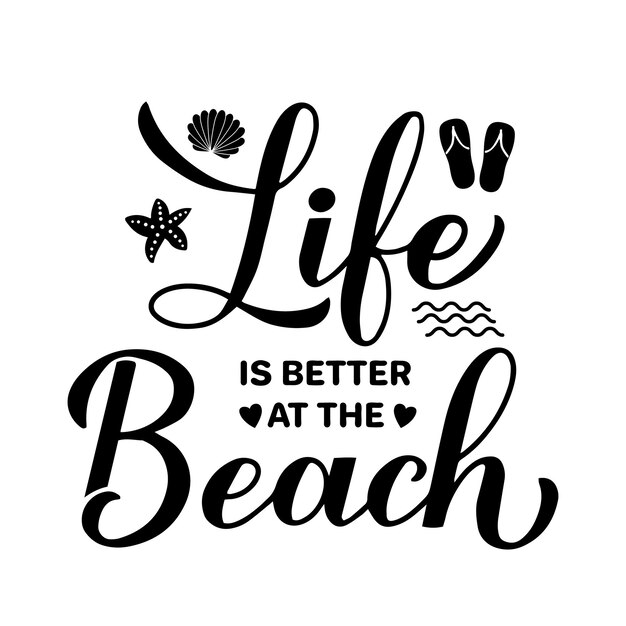
Życie na plaży odręczny napis tekst na białym tle z elementami projektu Typografia lato dla nakładek fotograficznych tshirt wydrukować projekt plakatu ulotki Plaża życie wiadomość